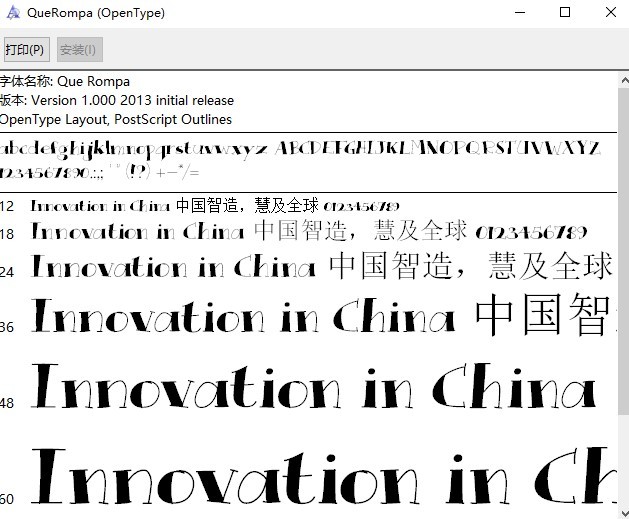
que rompa字體輸入的文字內(nèi)容非常有特點(diǎn),看起來卡通萌動(dòng),比較適合用來設(shè)計(jì)一些兒童題材的版面內(nèi)容,使用它輸出的文字看起來呆萌靈動(dòng)。整體式看起來很不錯(cuò)的喲。喜歡這個(gè)字體的朋友快點(diǎn)來安裝吧!
Que Rompa字體是一款用于細(xì)線設(shè)計(jì)方面的字體!這款字體使用范圍非常廣,可以用于排版設(shè)計(jì)、印刷等等。
2.字體有部分是加粗的
3.英文字體輸入很好看